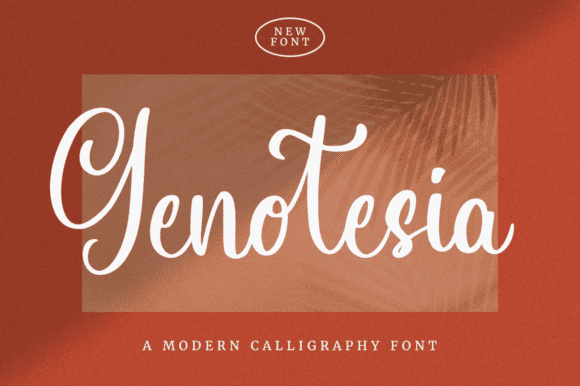
Название: Genotesia Font (2021)
Genotesia - это элегантность в одном простом шрифте, вдохновленном нестареющей классической каллиграфией.
Не слишком тонкий и не слишком толстый, сбалансированный и разнообразный, этот шрифт создан для того, чтобы подчеркнуть красоту ваших проектов.